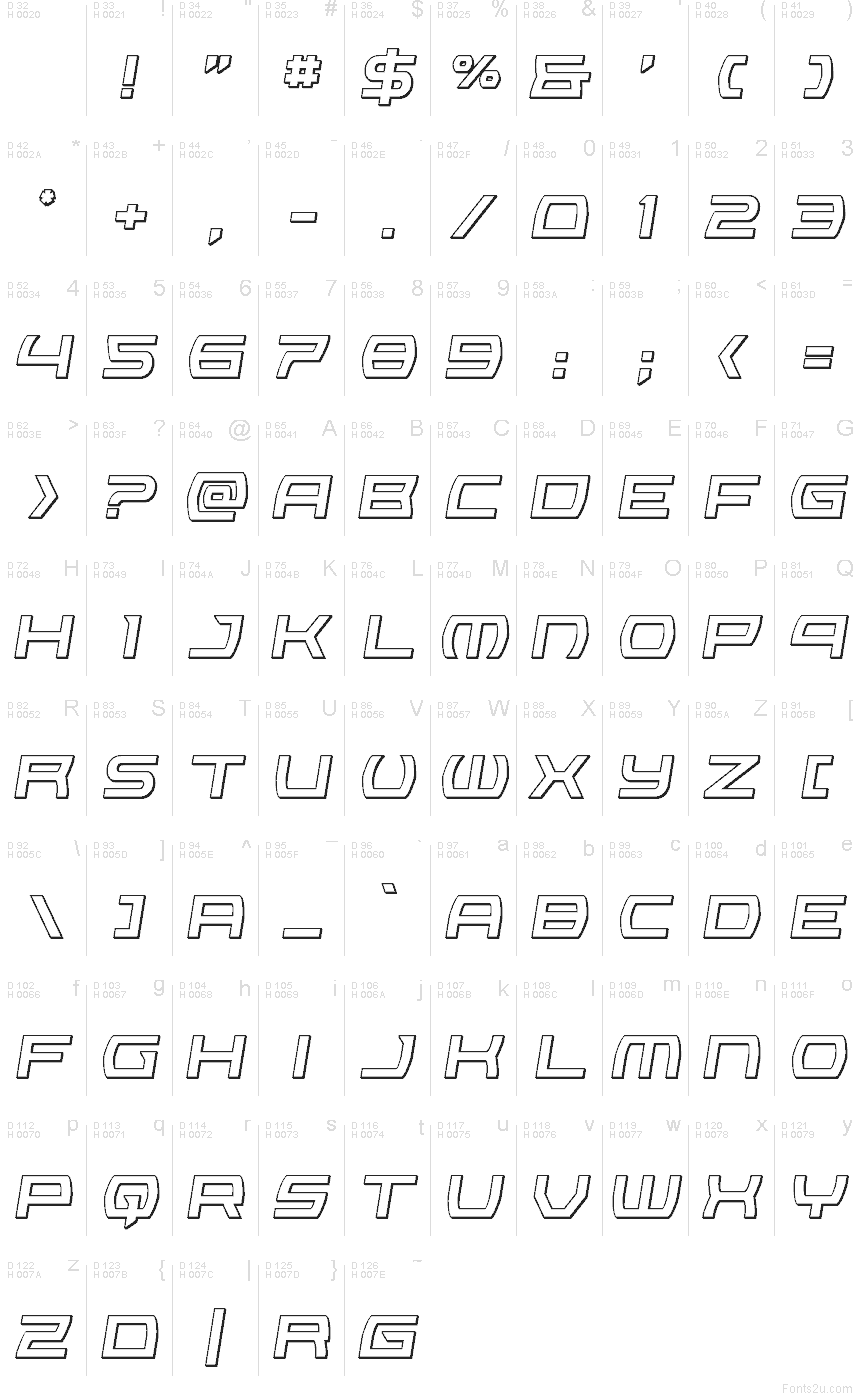
Icemaster 3D Semi-Italic von Iconian Fonts ist eine futuristische 3D-Display-Schrift mit einer glatten Optik, die an eine Eislauffläche erinnert. Die Buchstaben neigen sich dynamisch nach vorne und bestechen durch ihre breiten, abgerundeten Formen. Dank der versetzten Schattenlinie erhält das Alphabet eine präzise, maschinell wirkende Tiefe, die direkt an das Design retro-futuristischer Sci-Fi-Logos erinnert.
Diese kostenlose Schrift eignet sich ideal für Spieletitel, E-Sport-Branding, Plakatüberschriften, YouTube-Thumbnails und Titelkarten, bei denen ein schräger Chrom-Look die Stimmung perfekt einfängt. Auch für kurze Monogramme oder Abzeichen ist sie hervorragend geeignet, da die massiven Großbuchstaben und die integrierten, dreidimensionalen Kanten selbst kurzen Wörtern eine kraftvolle Präsenz verleihen.